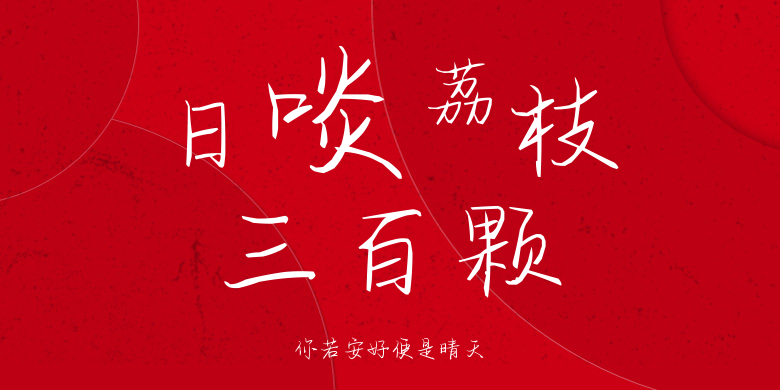
你若安好便是晴天
你若安好便是晴天,这款字体结构工整、笔画清晰,兼顾美观与易读性,适用于标题、正文、海报、包装、LOGO 等多种场景。字形优雅稳定,风格百搭耐看,适配日常排版与创意设计,让文字呈现更舒适、更具质感。你若安好便是晴天一笔一画,皆是细节,以均衡的比例、流畅的线条打造舒适视觉体验,字形端正大气,风格简约现代。无论是商业设计、品牌宣传还是日常排版,都能轻松驾驭,让文字更有格调与力量。你若安好便是晴天字体下载。